Trong hàng trăm, hàng ngàn tài nguyên thiết kế, bao gồm font chữ, có rất nhiều font chữ đẹp, thu hút và có thiết kế độc đáo. Nhưng đáng tiếc có không ít các font chữ đẹp đó lại không thể hiển thị chính xác khi gõ bằng tiếng Việt.
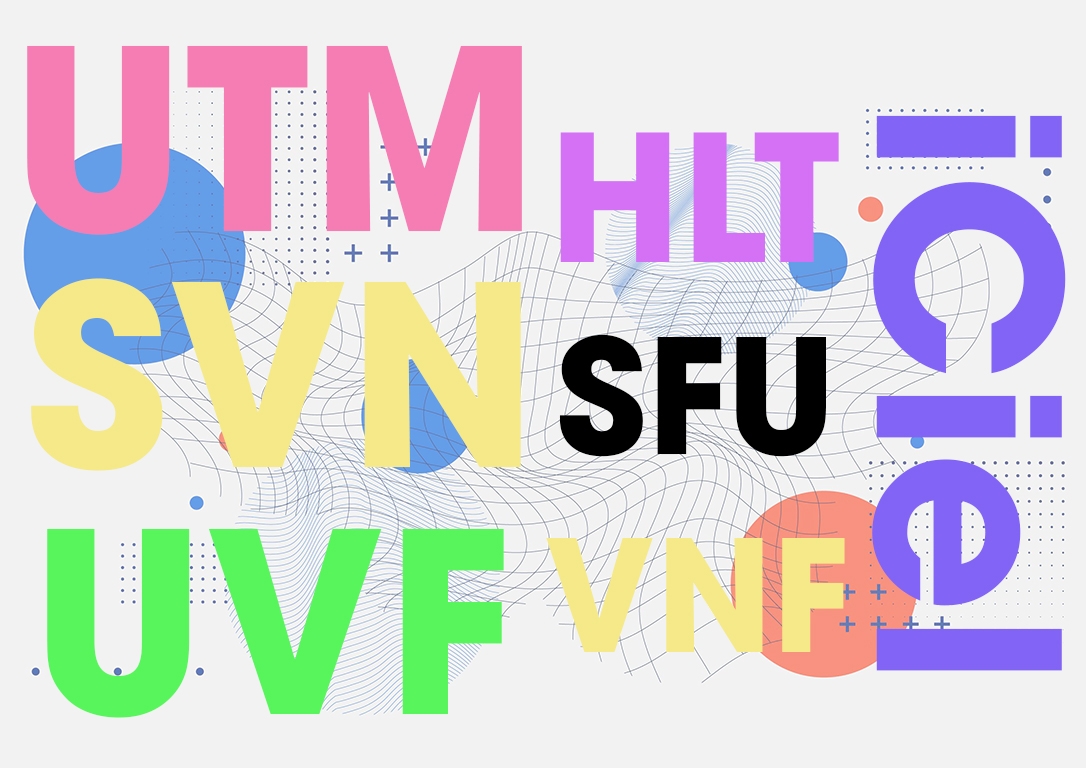
Hay gặp nhất là lỗi font chữ trong Word khiến văn bản rất khó đọc. Nguyên nhân vì các font chữ đó chưa được “việt hóa” 100%. Để sửa lỗi font chữ trong Word thì có lẽ chỉ còn cách dùng các font chữ đã được việt hóa. Do đó nhu cầu sở hữu các bộ font chữ việt hóa là rất lớn để phục vụ cho thiết kế, học tập hoặc làm việc.
Không phải bộ font chữ việt hóa nào cũng miễn phí cho người dùng. Sẽ có một vài font chữ việt hóa đặc biệt với nét chữ, kiểu chữ, độ đậm, mỏng nổi bật cần phải trả phí. Tuy vậy cũng có một số bộ font chữ việt hóa phổ biến và thông dụng đã được các nhà thiết kế và người dùng chia sẻ miễn phí rộng rãi.
Tổng hợp bộ font chữ việt hóa đẹp mắt và đa dụng
Họ font UTM
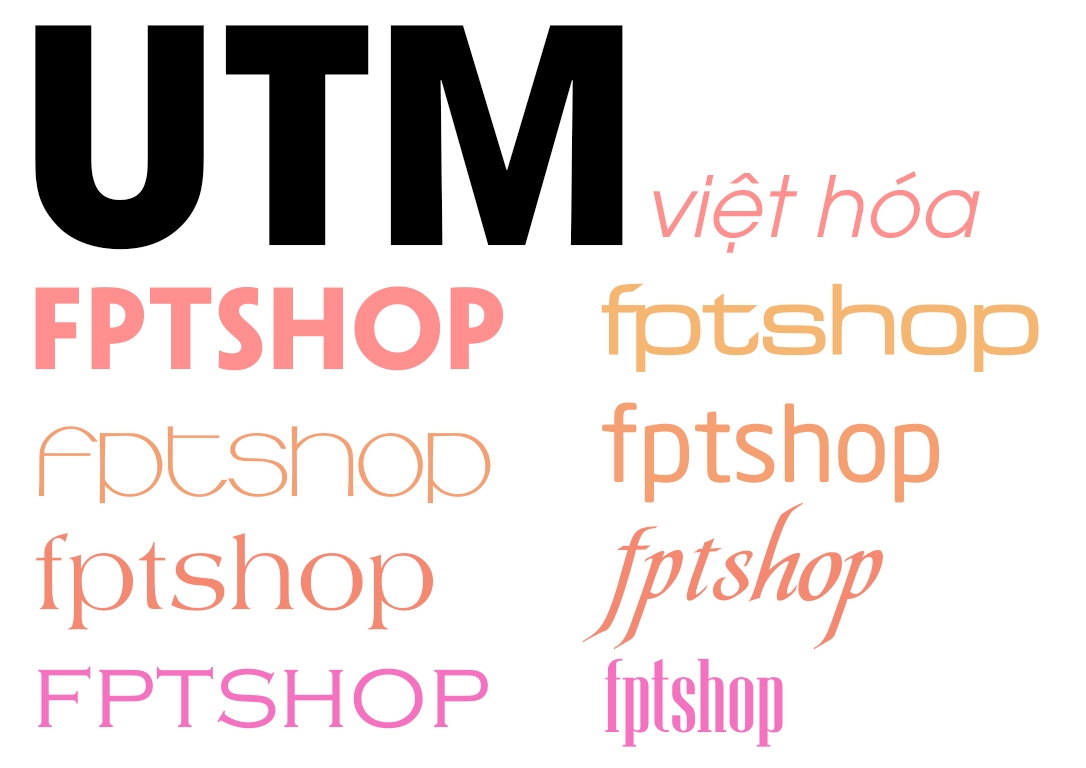
Bộ font UTM là font chữ tiếng Việt viết tắt của Unicode Thiên Minh với rất nhiều kiểu chữ độc đáo. Đây là bộ font chữ rất nổi tiếng đối với đa số dân thiết kế nội ngoại thất, thiết kế công trình.
Họ font SFU
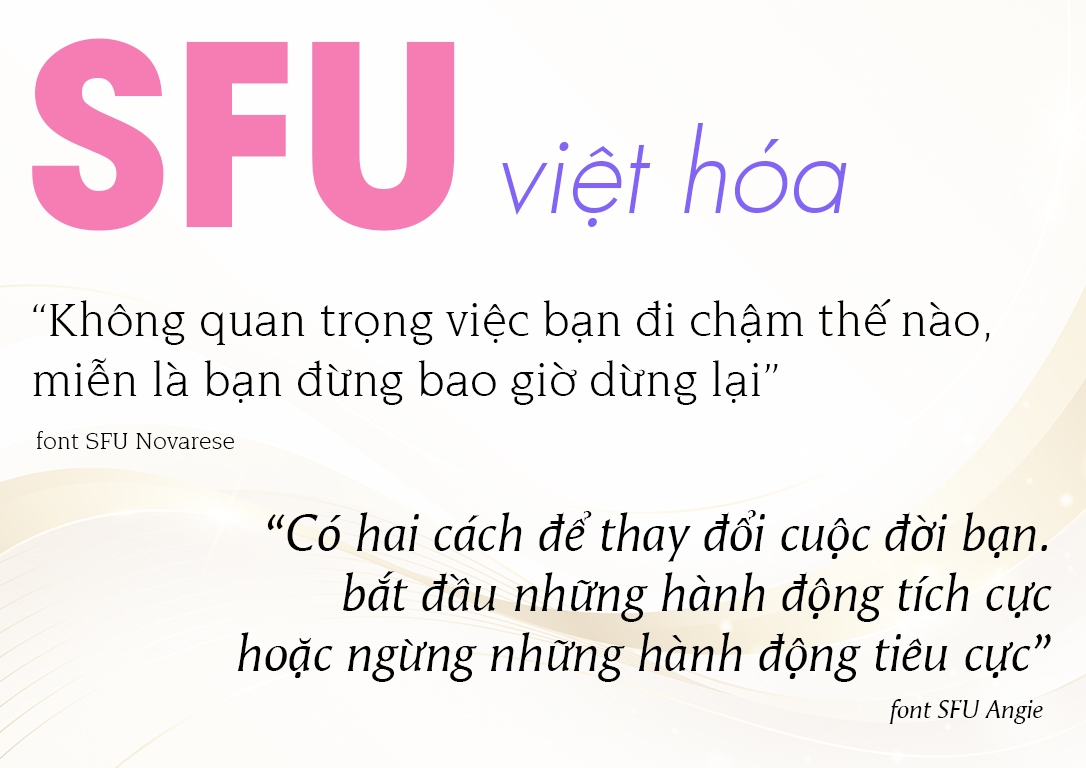
Một họ font chữ khá phổ biến trong thiết kế đồ họa và website nhờ tính thông dụng, phù hợp cho từng mục đích sử dụng khác nhau. Bộ font SFU này có chứa nhiều font Serif có chân khá đẹp, rất phù hợp cho thiết kế catologe, thư mời,…
Họ font HLT
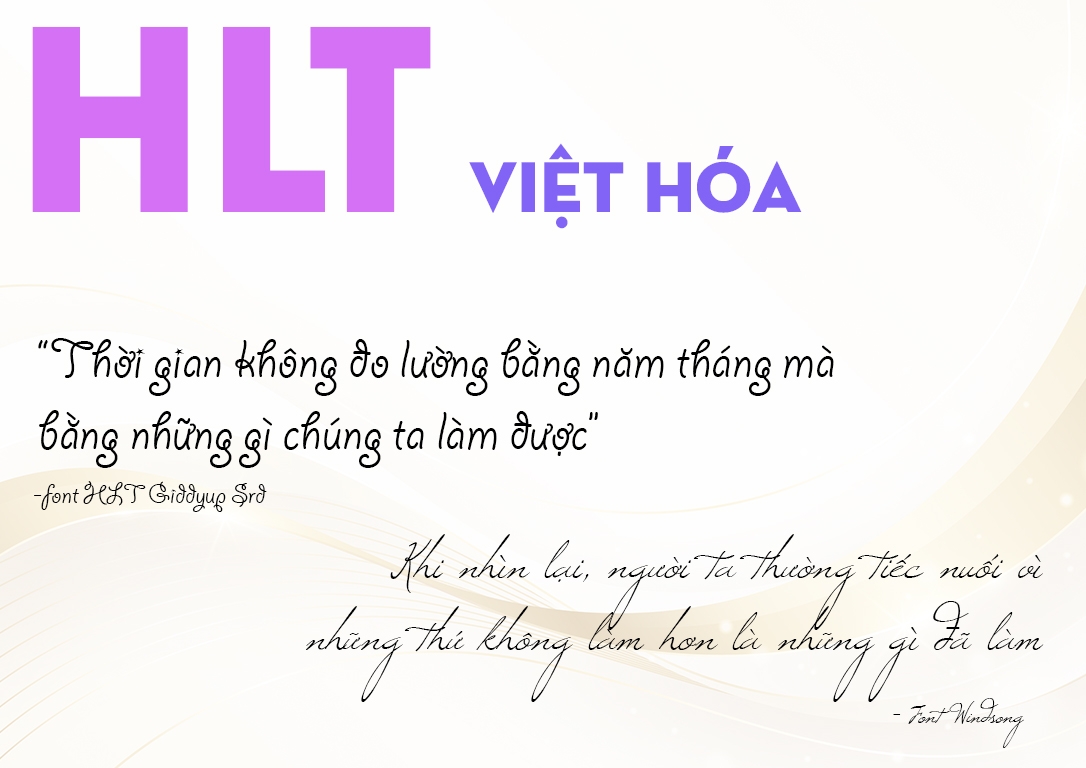
Bộ font HLT việt hóa khá nổi tiếng vì nó phù hợp cho các thiết kế cần sự sáng tạo, phá cách, độc đáo. Đó là bởi bộ font này chứa nhiều font chữ viết tay cách điệu hóa, font chữ cổ điển việt hóa có nhiều nét tạo sự mềm mại. Sẽ rất tuyệt vời nếu sử dụng font chữ này để tạo ra các bức ảnh chill, câu quote hay trên nền một bức ảnh đầy tâm trạng.
Họ font iCiel
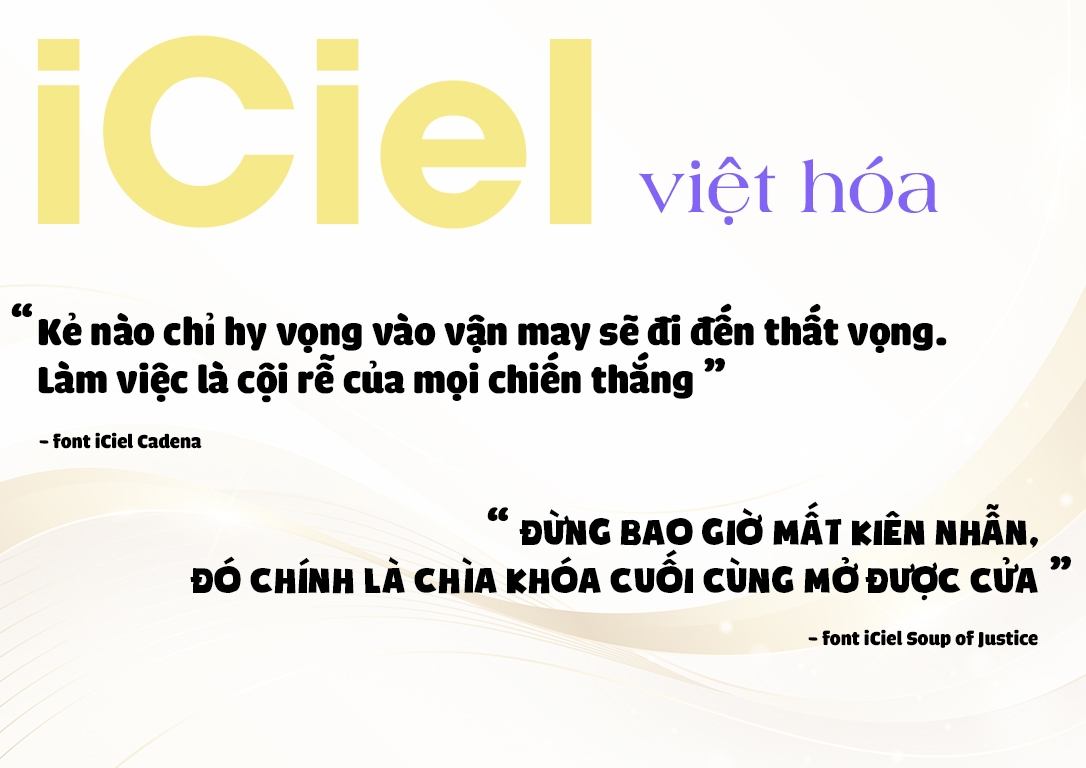
Đây là một trong những font chữ việt hóa có tính ứng dụng cao trong thiết kế. Tuy nhiên thực tế iCiel không phải là tên một bộ font là thực chất là một diễn đàn chuyên về thiết kế và việt hóa font chữ nổi tiếng.
Cộng đồng này là nơi mà những người đam mê với đồ họa, thiết kế đóng góp các font chữ việt hóa miễn phí cho đông đảo người dùng. Thường thì họ font iCiel sẽ có tiền tố iCiel ở đằng trước, sau đó đến tên gốc của font nước ngoài được việt hóa.
Họ font SVN
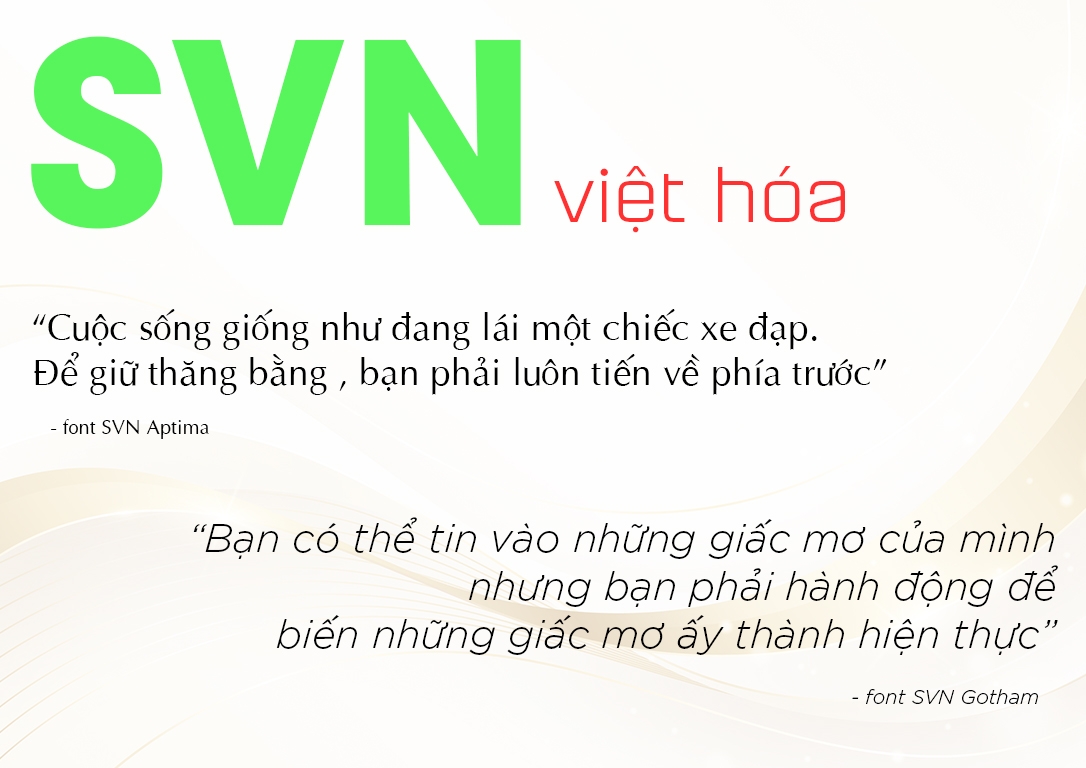
Bộ font việt hóa SVN sở hữu thiết kế đặc sắc cung cấp cho người dùng những lựa chọn về font chữ để thiết kế, soạn thảo tài liệu hiệu quả và chuyên nghiệp. Một số font SVN đẹp có thể kể đến như SVN Gotham hay SVN Harmony, SVN Helvetica. Trong đó font Helvetica được đánh giá khá cao vì tính ứng dụng trong các văn bản truyền thống, thậm chí là cả logo của nhiều thương hiệu lớn như Panasonic, BMW, Toyota, American Airlines,…
Họ font UVF
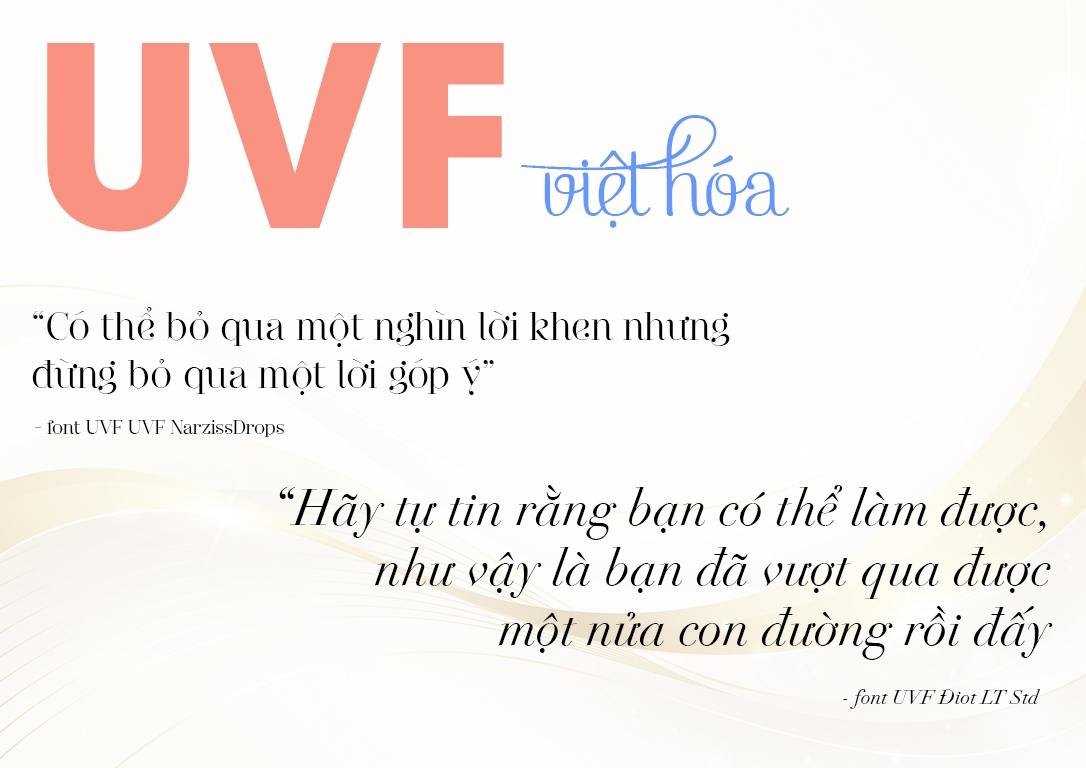
Với dân thiết kế thì hẳn không thể không biết họ font việt hóa UVF. Họ font việt hóa UVF có nhiều font khá đẹp như font chữ viết tay Voyage, Slim Tony, Blenda Script và rất nhiều font chữ cổ điển việt hóa khác…rất phù hợp để bạn ứng dụng và tạo ra được các tác phẩm thiết kế, logo, banner, poster thu hút, ấn tượng với người xem.
Họ font VNF
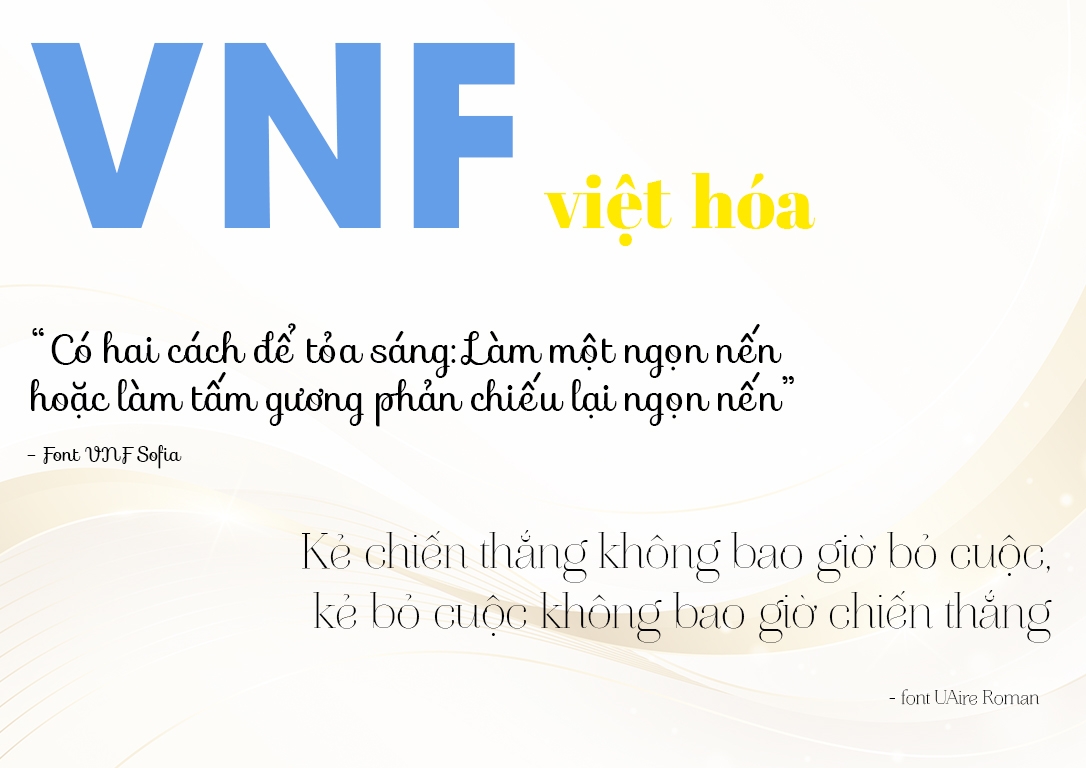
Đây là một họ font việt hóa khá phổ biến với các font như VNF Shelia, VNF-Buttermilk, VNF-Sofia, VNF-Valentina. Đây đều là các font chữ phù hợp để thiết kế các bức ảnh tâm trạng, truyền cảm hứng, poster, banner đẹp.